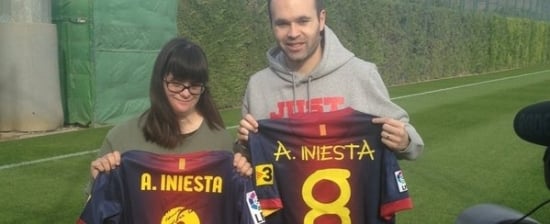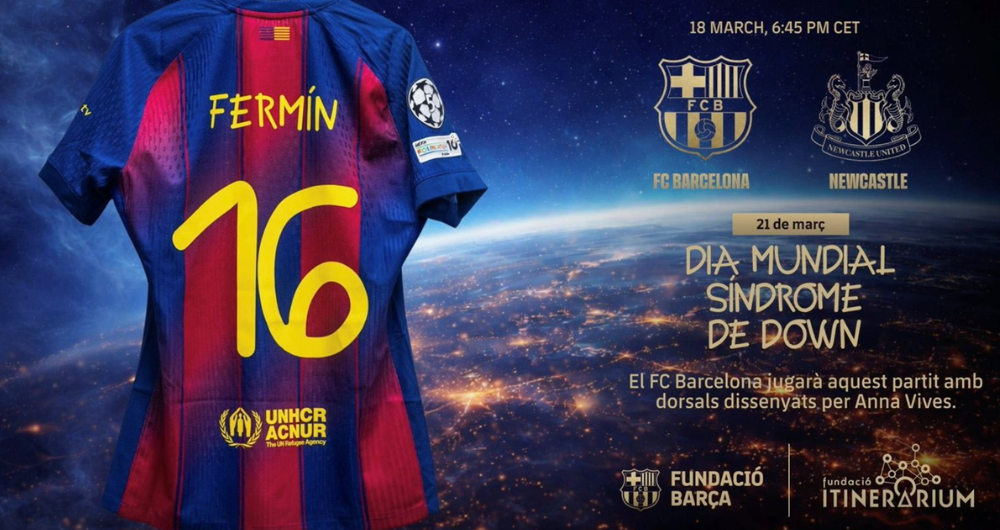
FC Barcelona incorpora tipografía inclusiva en la Champions League por el Día del Síndrome de Down
FC Barcelona incorpora tipografía inclusiva en la Champions League.
La acción se activará en el partido contra el Newcastle, donde el equipo utilizará una tipografía especial en sus camisetas como parte de una iniciativa de sensibilización impulsada por su fundación en el marco del 21 de marzo.
El FC Barcelona activará una iniciativa de impacto social en el marco de la UEFA Champions League. El club utilizará una tipografía inclusiva en las camisetas de sus jugadores durante un partido oficial, como parte de una acción vinculada a la visibilidad de personas con discapacidad intelectual y el Síndrome de Down.
La intervención se enmarca en las actividades por el Día Internacional del Síndrome de Down y cuenta con el respaldo de la Fundación FC Barcelona, que lidera la ejecución del proyecto junto a aliados institucionales.
FC Barcelona y el diseño con propósito en el escenario deportivo
La acción introduce una tipografía creada por Anna Vives, una joven con síndrome de Down, quien desarrolló este proyecto con el objetivo de promover la inclusión social a través del diseño. Su propuesta se basa en una reinterpretación del alfabeto que busca representar diversidad y reforzar la idea de integración.
El club aplicará esta tipografía en los dorsales de los jugadores durante el partido con Newcastle correspondiente a la fase eliminatoria del torneo continental. Asimismo, esta ejecución marca la primera vez que este recurso visual se integra en una competición de este nivel, lo que amplifica su alcance a audiencias internacionales.
La iniciativa también contempla su réplica en el equipo femenino del club, en el encuentro contra el Real Madrid el 2 de abril, lo que refuerza la consistencia de la acción dentro de la estrategia institucional. Además, distintas organizaciones y clubes de otras regiones adoptarán la tipografía en fechas cercanas, extendiendo el impacto más allá del contexto local.
Cabe mencionar que, el proyecto de Anna Vives tiene una trayectoria previa. La diseñadora inició el desarrollo de esta tipografía a inicios de la década pasada y logró su digitalización completa, lo que permitió su uso en múltiples soportes. Desde entonces, el recurso ha alcanzado difusión global con más de 15 millones de descargas en distintos países, lo que evidencia su adopción en entornos tanto culturales como corporativos.
En el caso del FC Barcelona, no se trata de una colaboración inédita. El club ya había integrado esta tipografía en una acción anterior durante un partido amistoso, lo que muestra continuidad en su enfoque hacia iniciativas de impacto social. Esa experiencia previa sentó las bases para su implementación en un escenario competitivo de mayor exposición.
Anna junto a Andrés Inista, que sujeta una camiseta del FC Barcelona con la tipografía de la joven.
La activación también involucra la presencia de la creadora en el estadio, donde participará de la jornada contra el Newcastle junto a representantes institucionales del club.